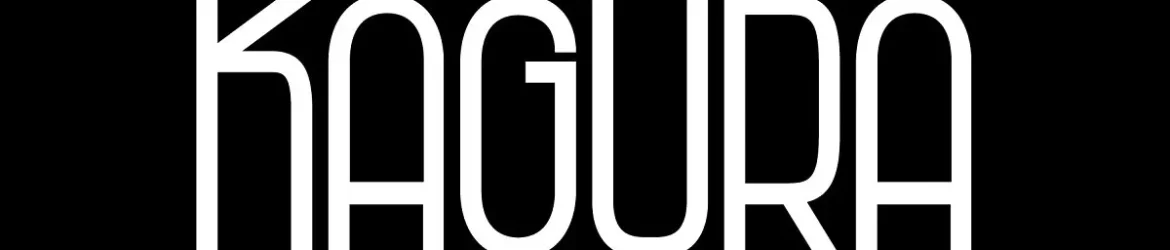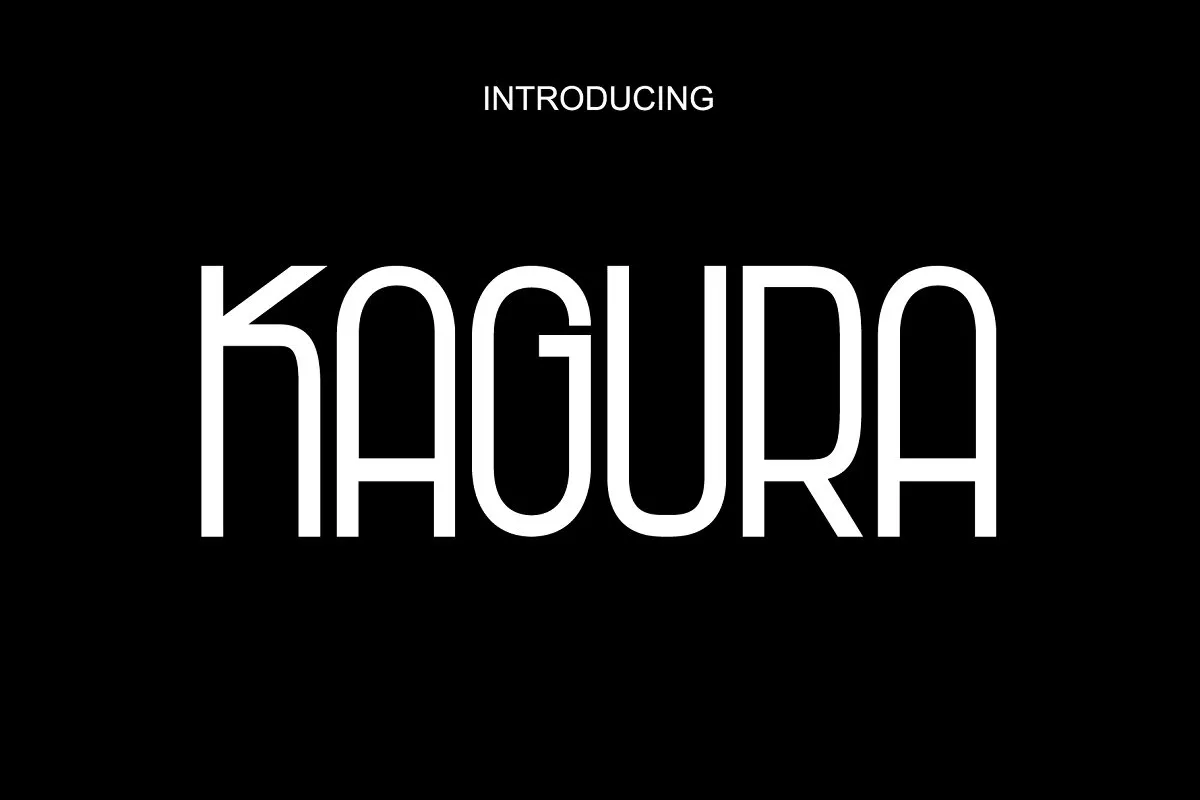
Kagura Sans Serif Font
Introduzimos Kagura Sans Serif Font, uma elegante sans serif com linhas altas e um aspecto sedutor. Ideal para designers que buscam criatividade e sofisticação, ela combina perfeitamente com ambientes de blogue alegres e modernos. Além disso, o seu design é ideal para criações visuais pessoais, como logomarcas ou bordas lindas para os seus espaços domésticos. Kagura também é uma ótima escolha para pequenas empresas, capa de livros, material educacional, revistas e comunicações comerciais – a lista pode realmente acabar aqui!